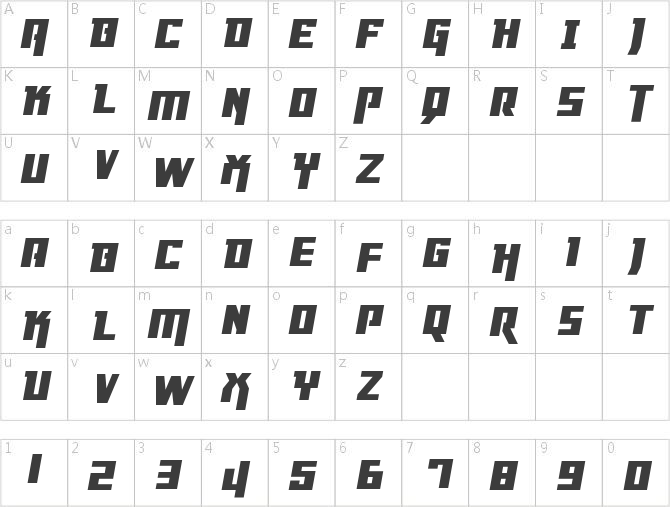
dangerflightexppandital
dangerflightexppandital介绍
dangerflightexppandital字体字库是一款让人赏心悦目、百看不厌的英文字体,适合各类广告和产品包装设计应用,字体大小0.02MB,格式为ttf字体,上传用户是sygyve520,作者/版权方为未知